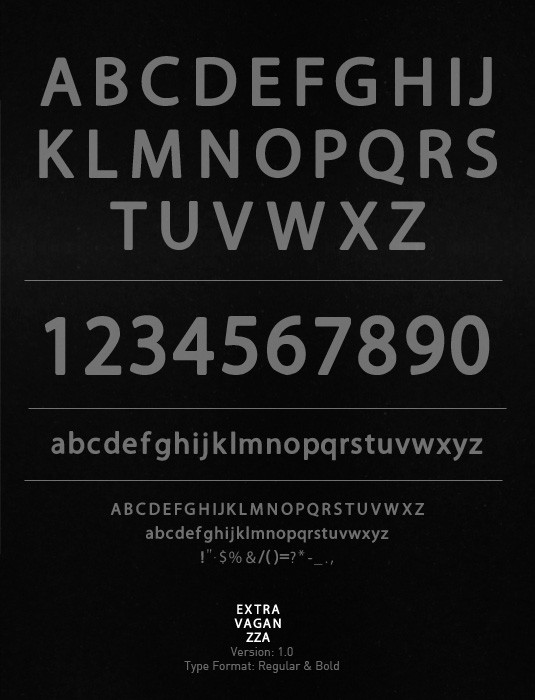
Inquietto β€” Extravaganzza font
Description Elegante tipografΓ­a en dos formatos: Regular y Bold.
Eegant fontype in two formats: Regular and bold
Perfect font to replace the comic sans one.
Has nice curvy edges and not too exaggerating as well. Great for typing paragraphs. Will be very useful. Thanks.
Reminds me of Futura.
elegant, i love the space between the letters!
looks like myriad...but a slight bolder...
very elegant!!